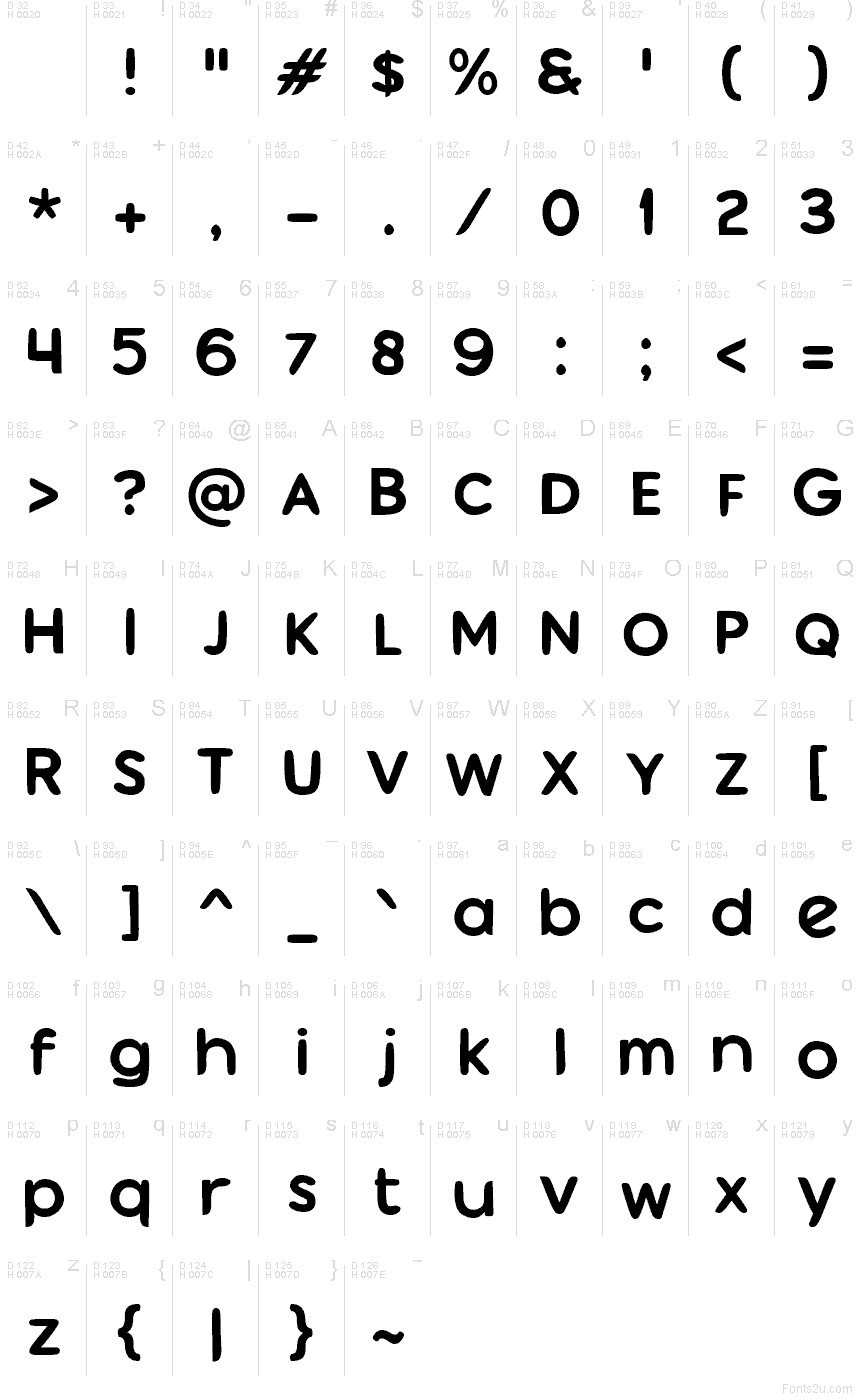
Ubahin od Wep je bezplatné bezpätkové písmo typu display s oblými verzálkami, mäkkou, buclatou siluetou a príjemným retro nádychom. Písmená pôsobia odľahčene a výrazne, so širokými krivkami, oblými spojmi a otvorenými tvarmi, vďaka ktorým si celok zachováva hravú náladu, bez toho aby pôsobil príliš prísne.
Hodí sa pre plagátové nadpisy, branding pre deti, obaly, titulky a krátke logotypy, kde potrebujete bezplatný font, ktorý dodá teplo bez toho, aby pôsobil presladene. Vďaka jednoduchosti a váhe verzálok funguje UBAHIN skvele aj pre monogramy a krátke texty, najmä ak hľadáte veľký, ľahko čitateľný rytmus namiesto ostrej dramatiky.
Ubahin
Prezentácia a vizuálna ukážka písma UBAHIN